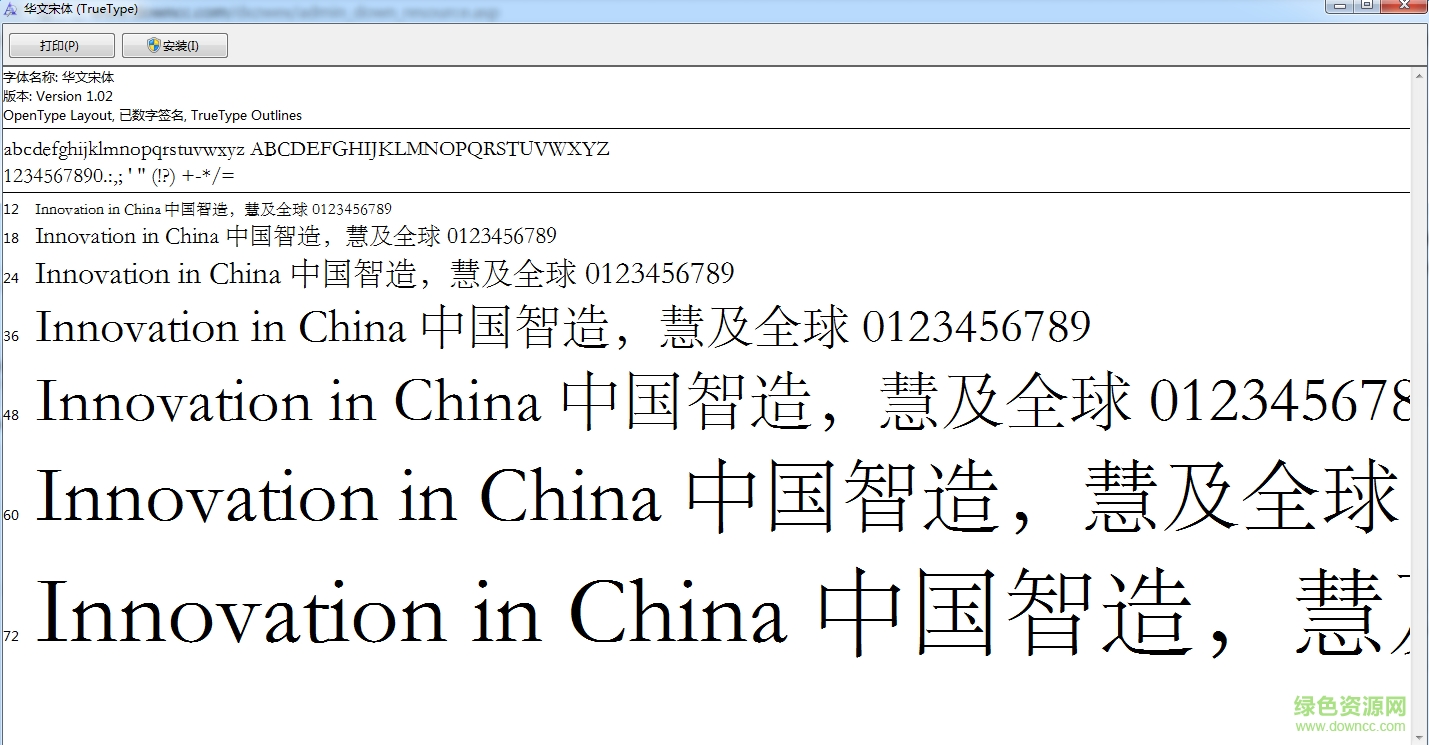
stsongti sc regular字体就是宋体简常规体,该字体重心平稳,端正大方,即美观又实用,需要该字体的朋友快来绿色资源网下载吧!
宋体起源
宋体是中国明代木版印刷中出现的字体。最初是在复刻临安书棚本时将笔划加以直线化,呈现出硬朗表情的一种字体。嘉靖三十二(1553年)刊刻的《墨子》中宋体的基础已经成型。明朝后期的万历年间刊本数量急速增加,促进了书籍制作的分工化。
字体适用领域
该字体适合性非常强,可应用于广告设计、名片设计、包装印刷、产品设计、网页设计、包装设计、 屏幕显示等等领域!